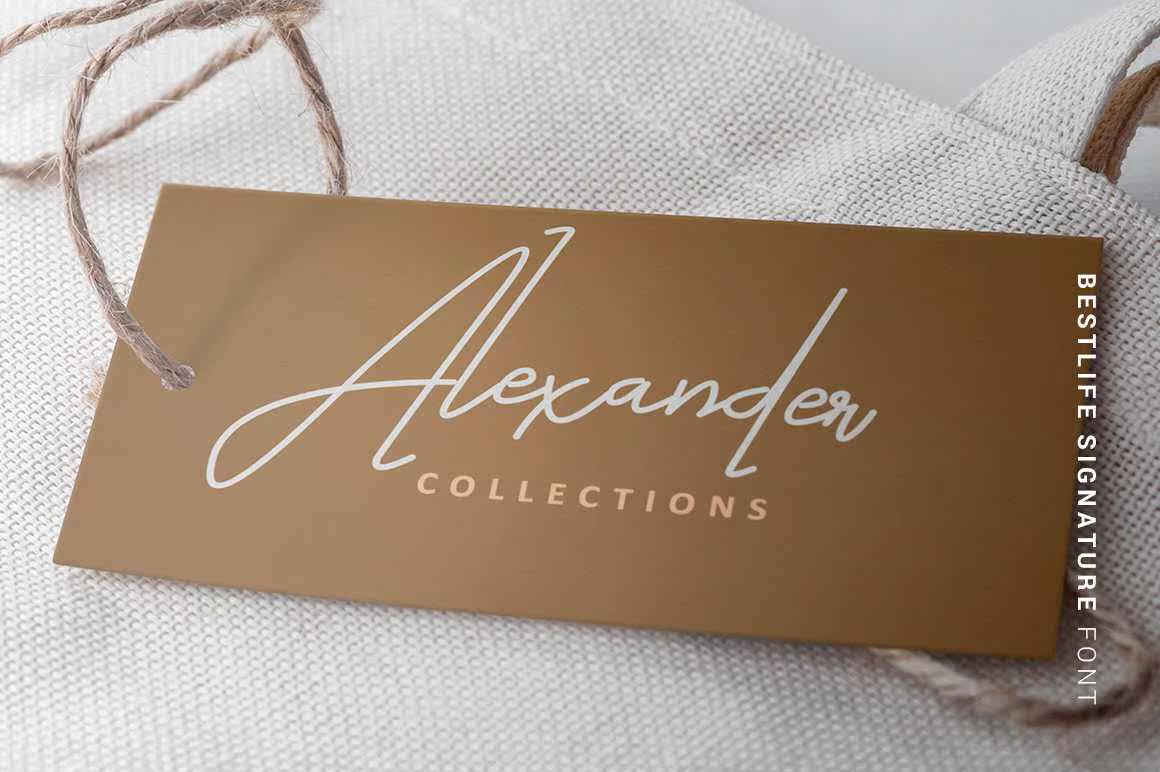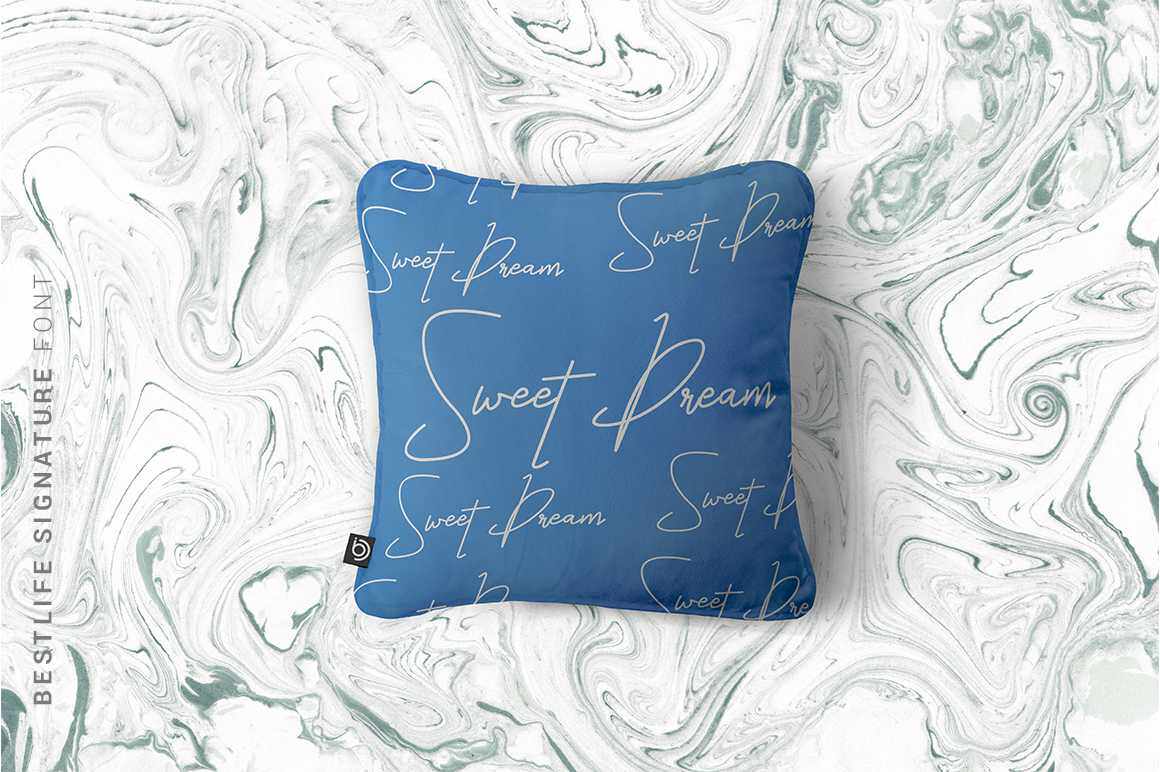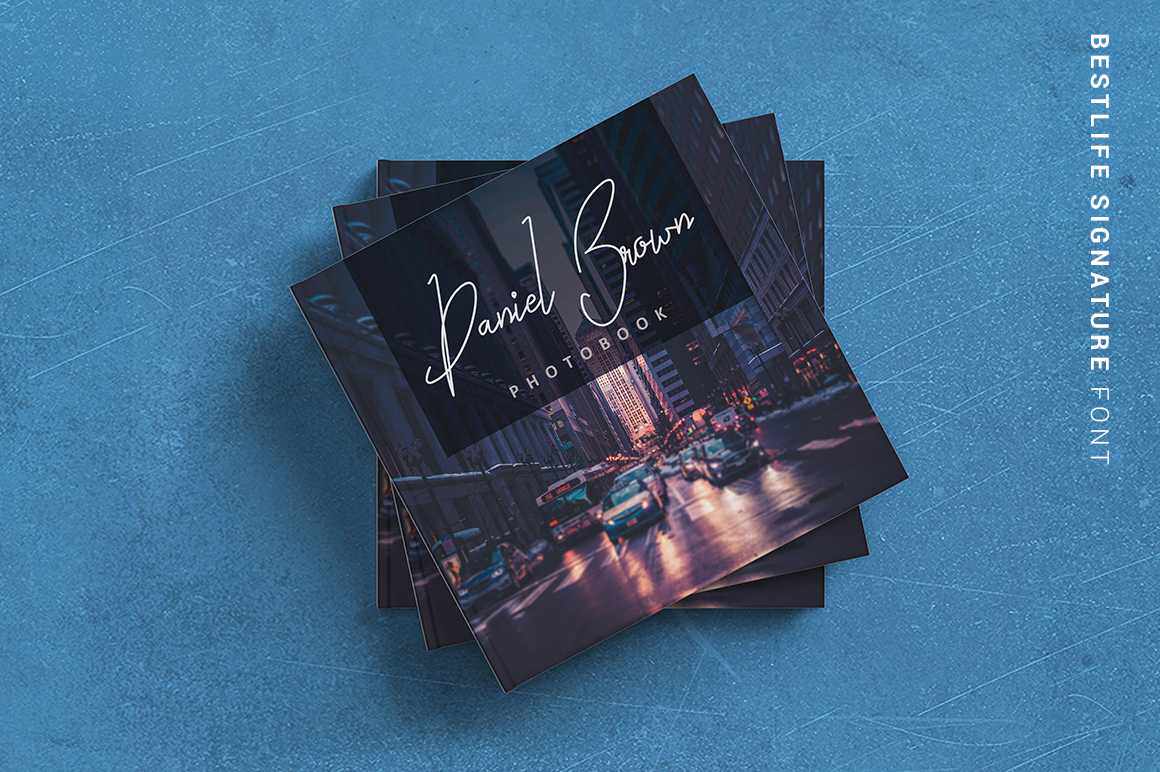
BestLife是一本带有自然和风格流的手写手稿。这本手稿集是个人品牌的完美之作。它的目的是让摄影师将其视为其摄影业务的一个标记,即“肖像”。但是,此作品适用于所有应用。从个人品牌推广、婚礼宣传到广告宣传的所有内容都可以从本签名集中获益。BestLife是一本具有自然和风格流的手写手稿。本签名集是个人品牌推广的完美之作。它旨在让摄影师成为其摄影业务的标志——因此名称为“肖像”。但是,这项工作适用于所有应用。从个人品牌和婚礼宣传到广告宣传,一切都可以从这一系列签名中受益。